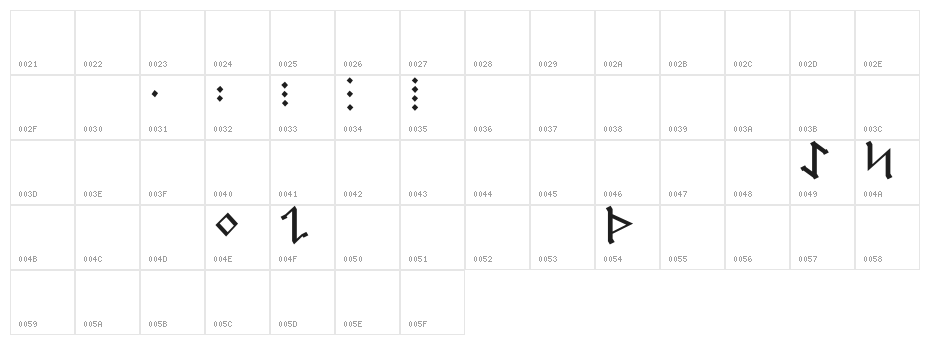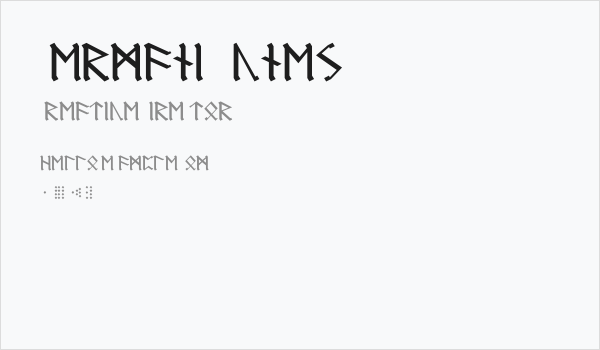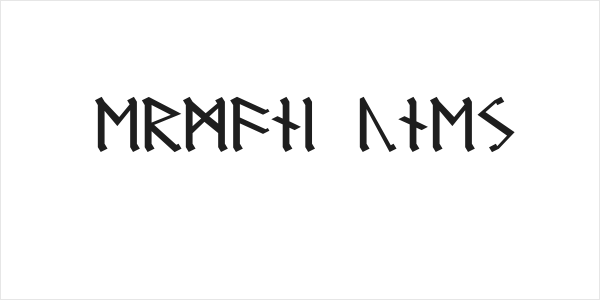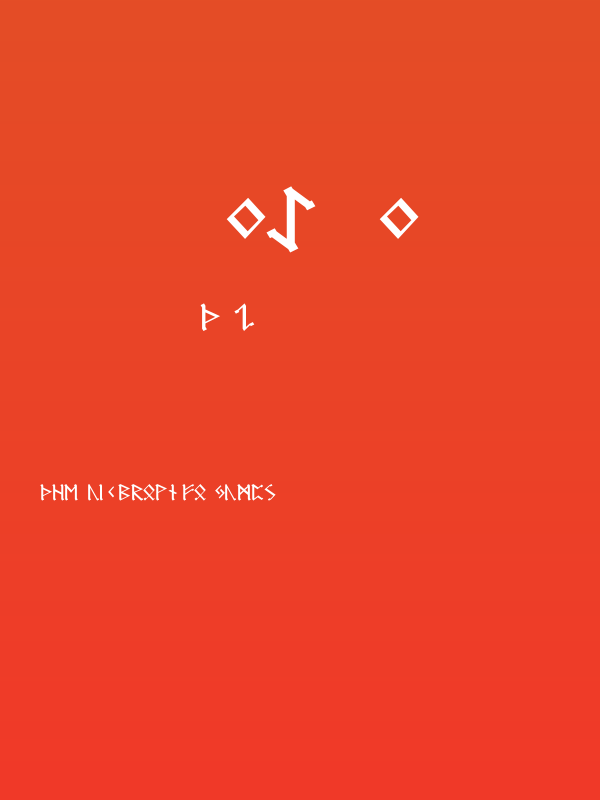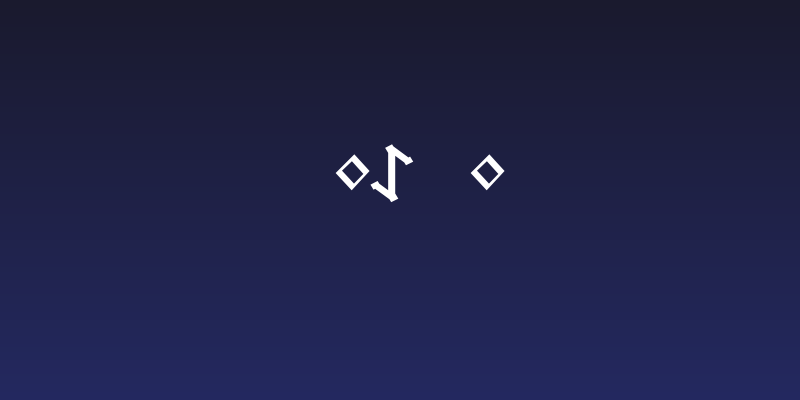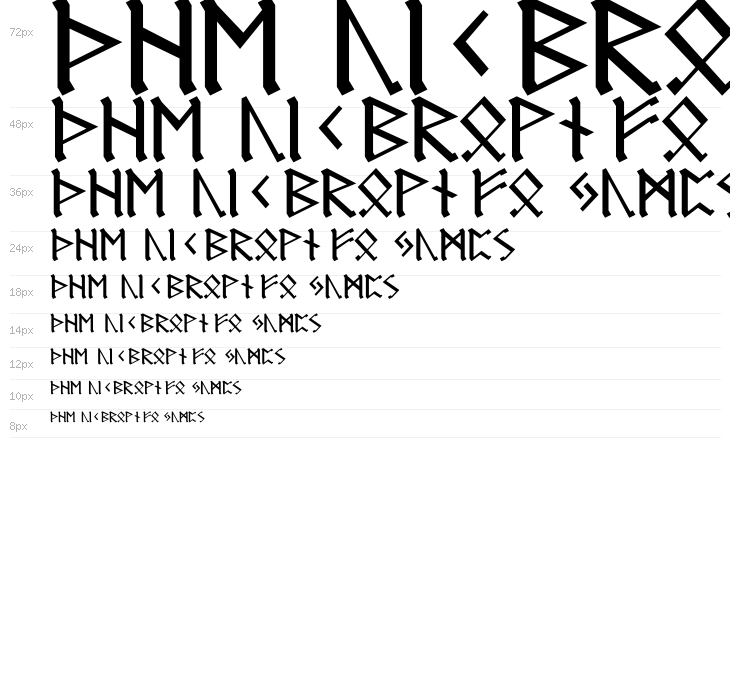
Germanic Runes Font
| Caso de uso | Logos, Headlines, Themed designs |
| Projetos propostos | Perfect for historical reenactment materials, fantasy book covers, themed event invitations, or cultural exhibitions. |